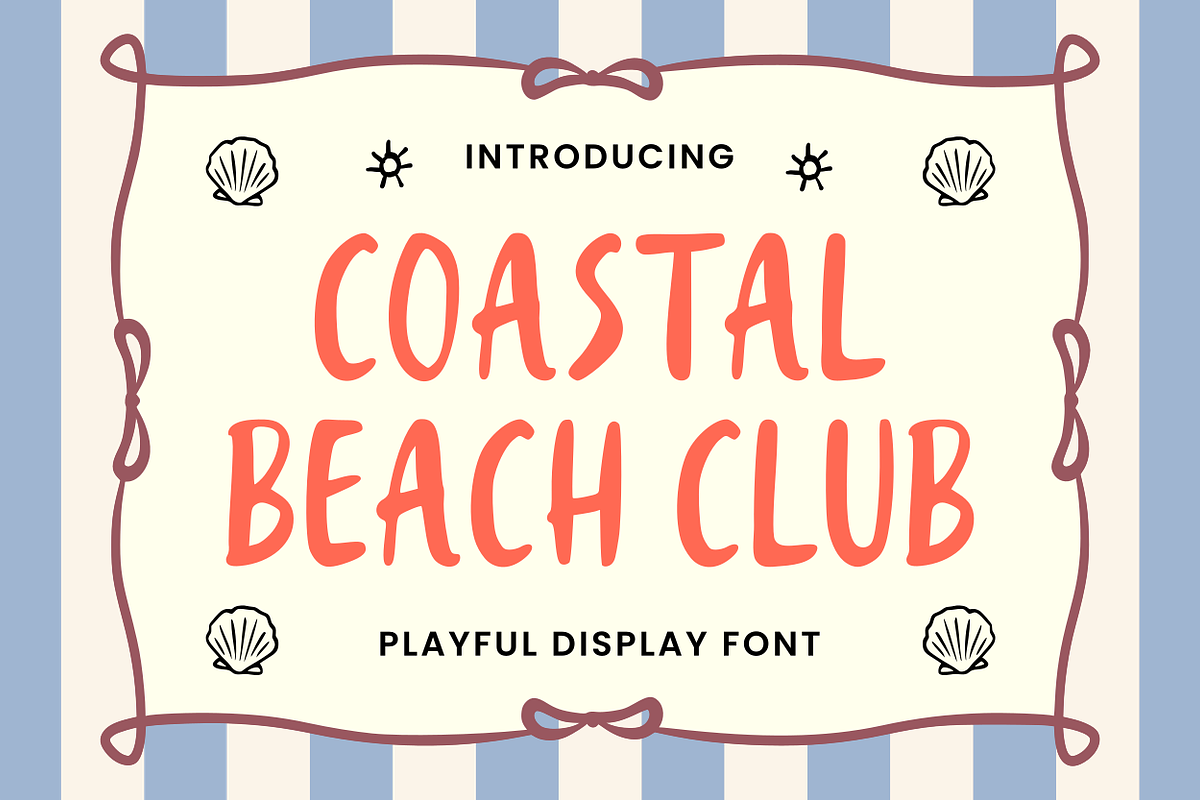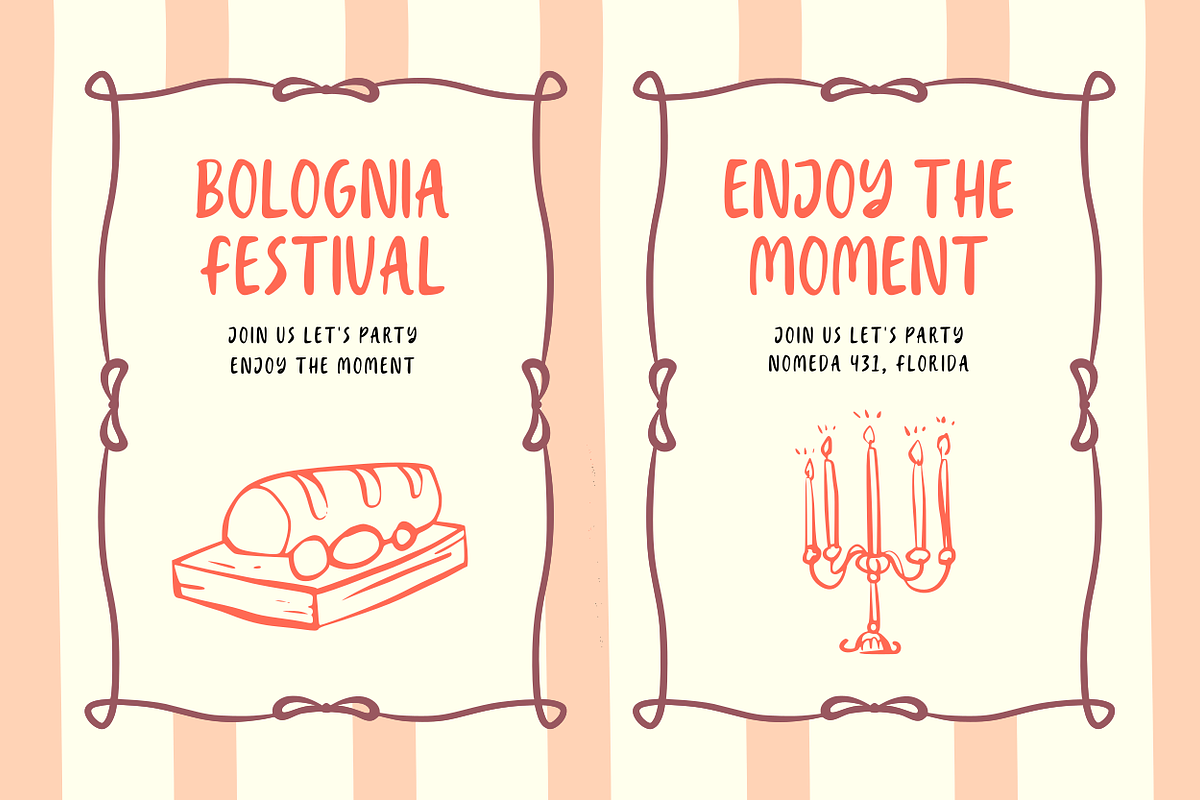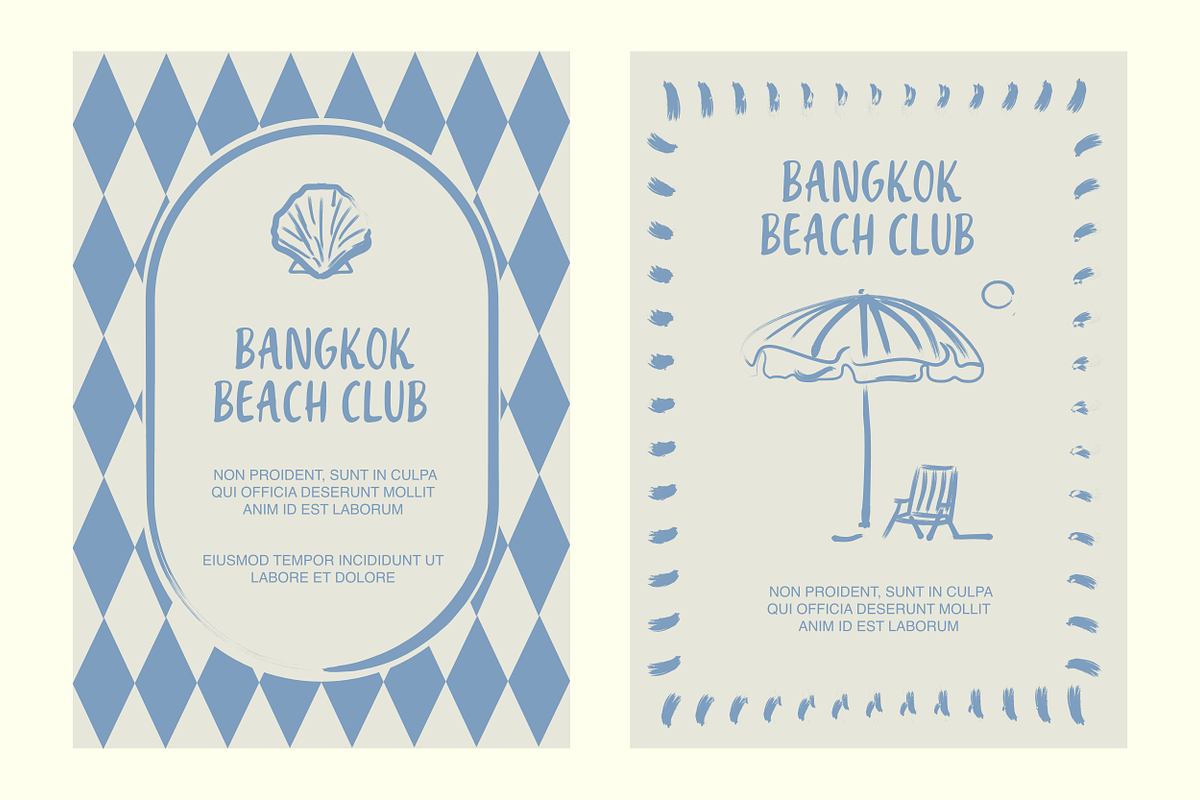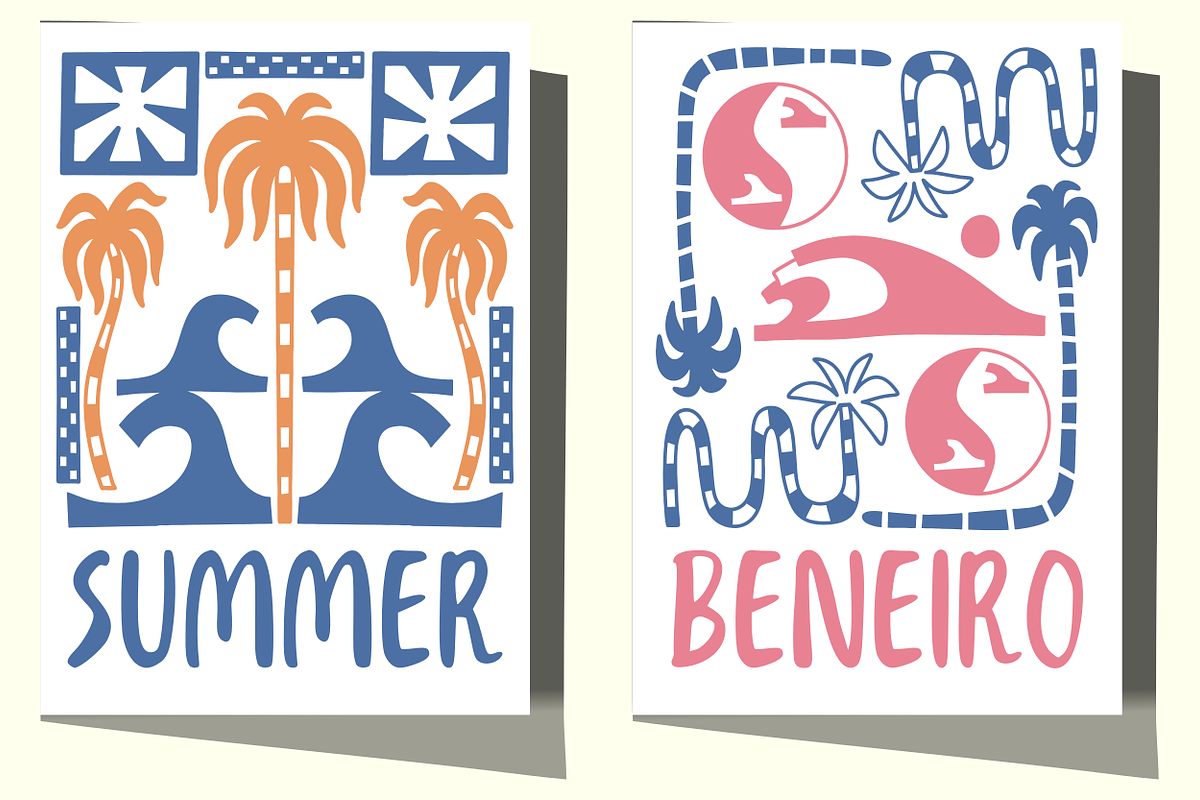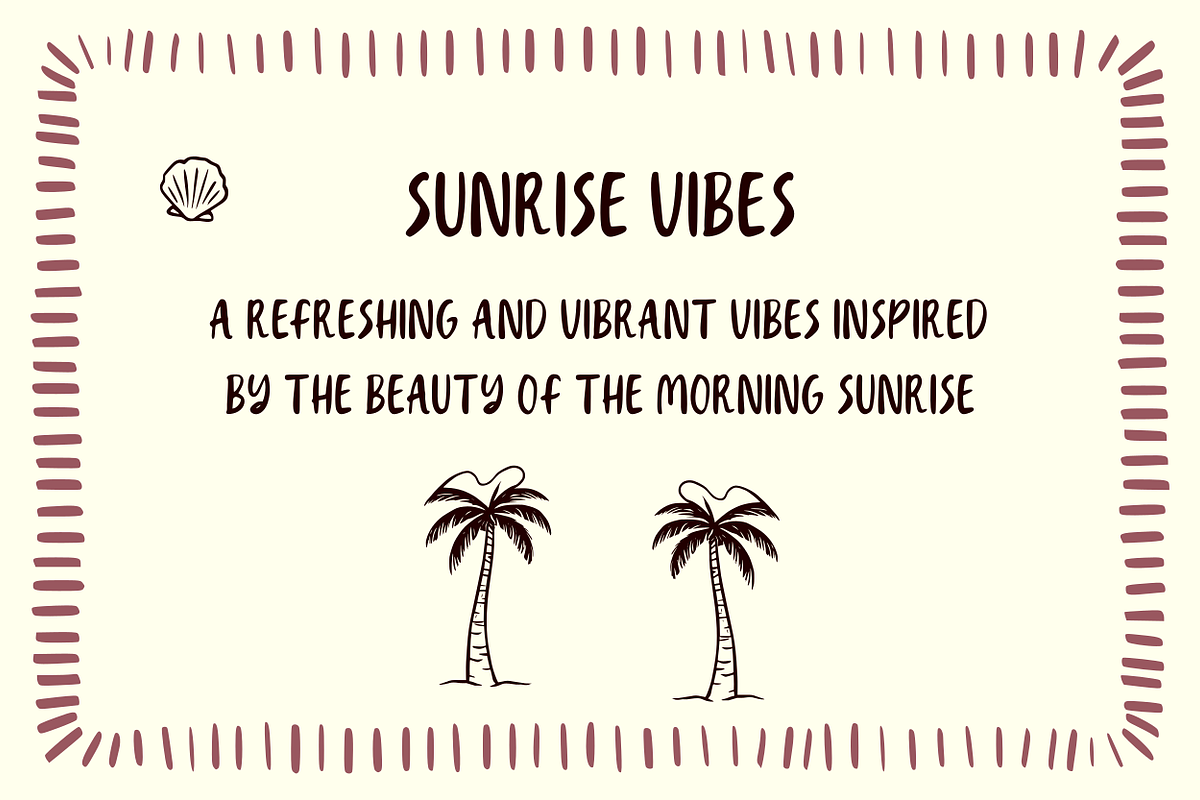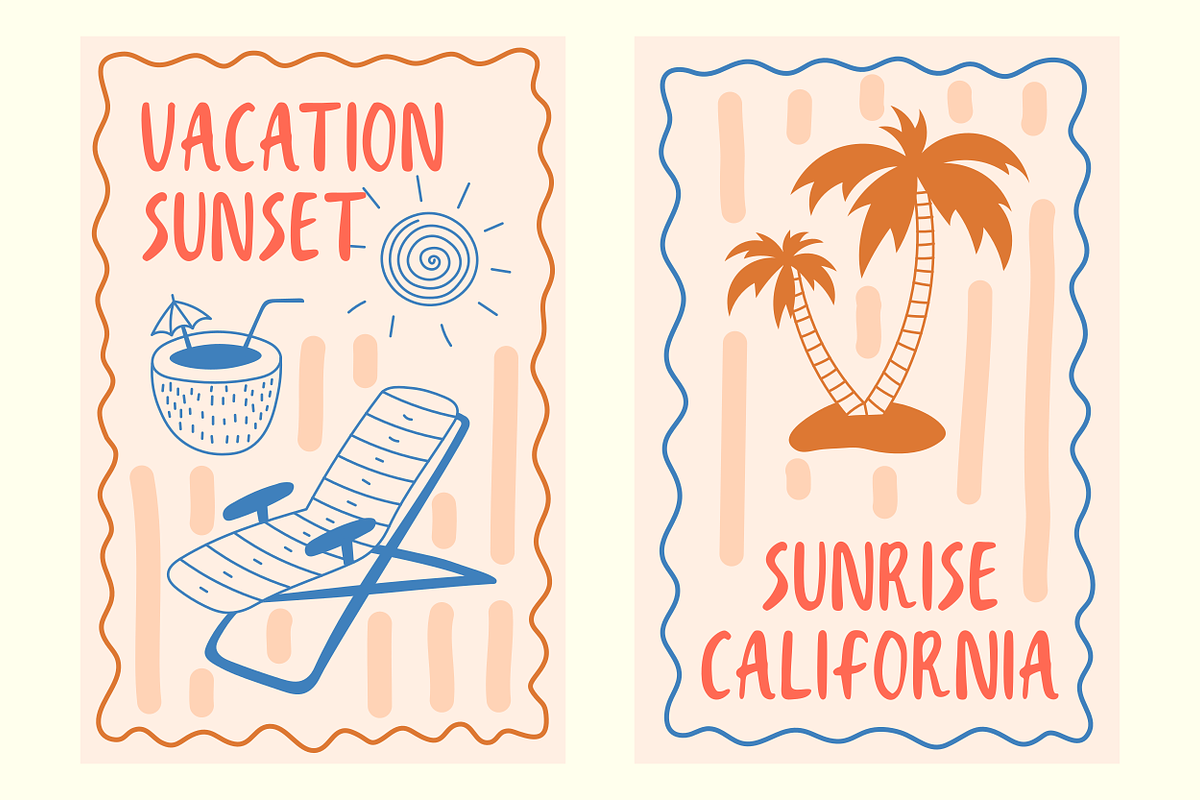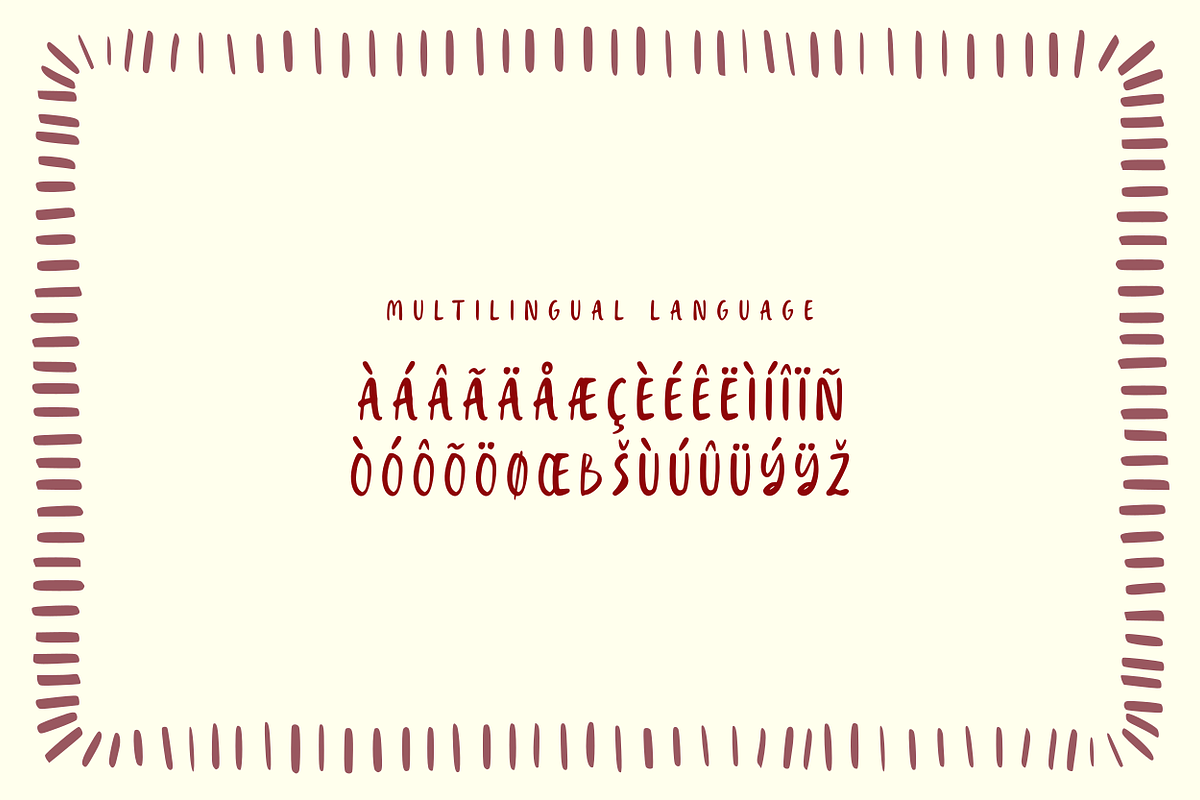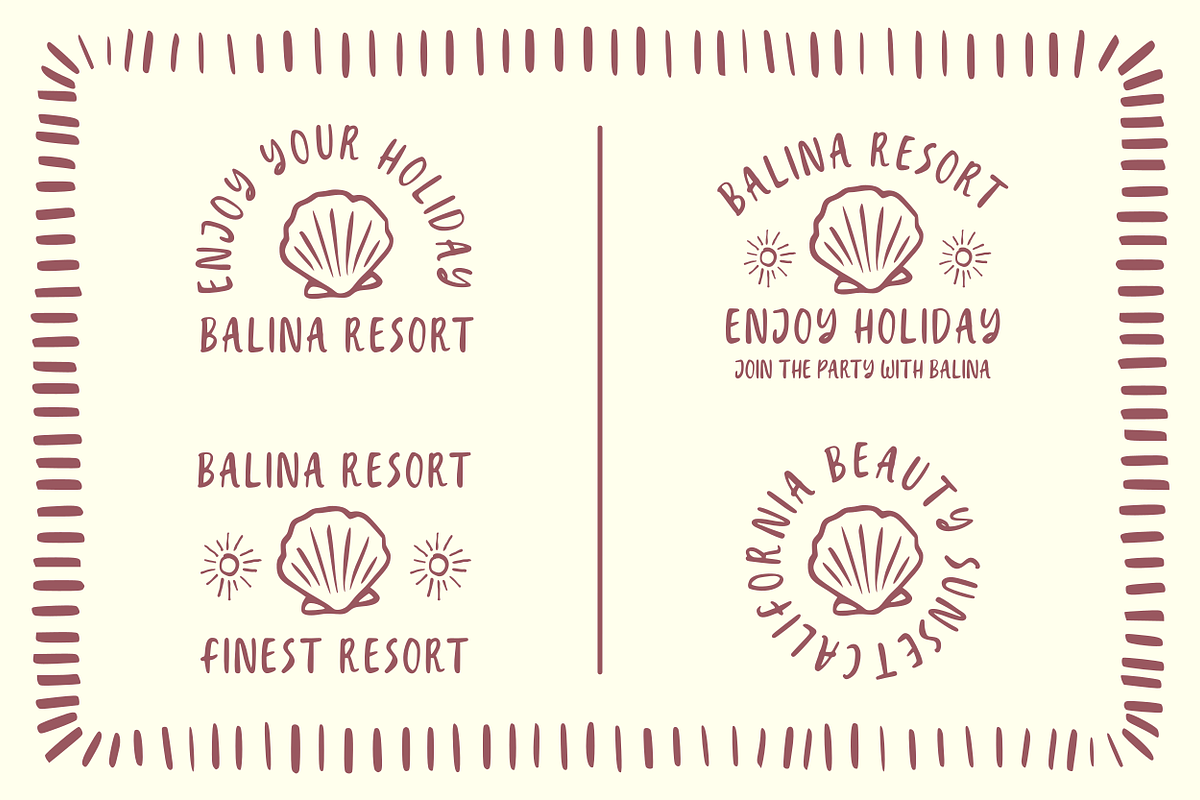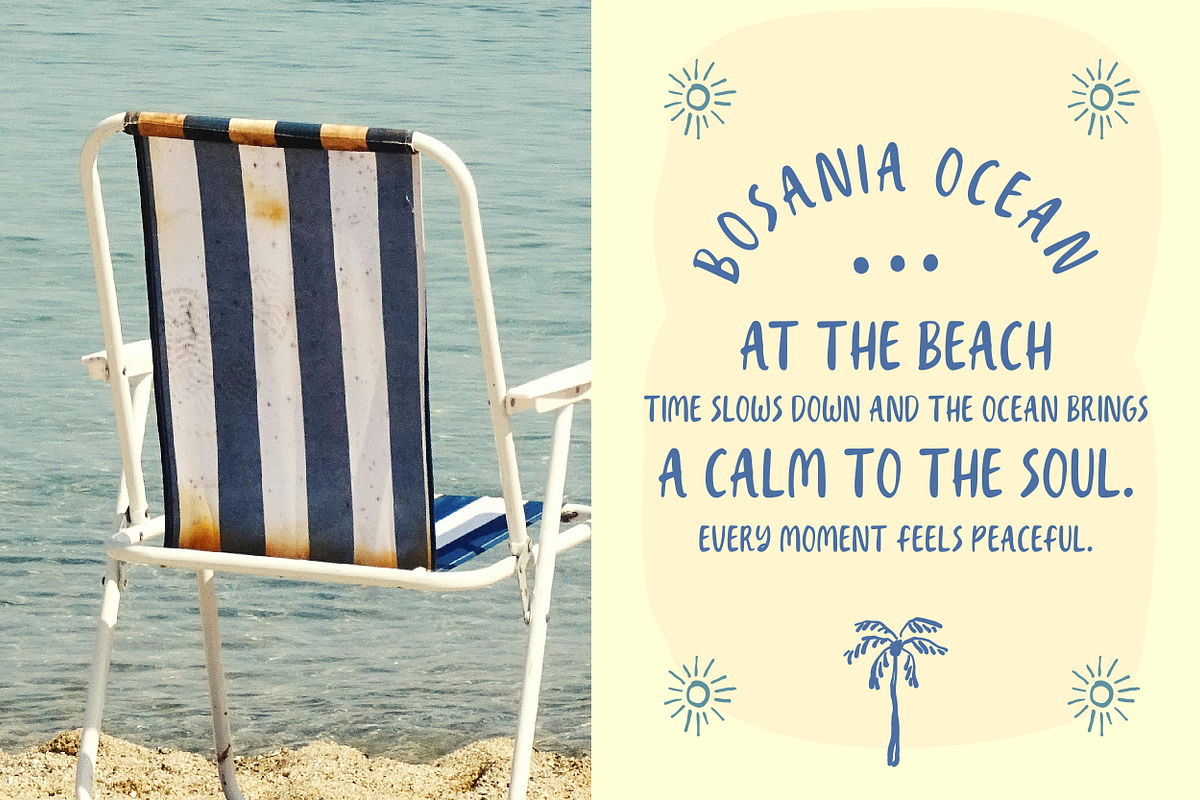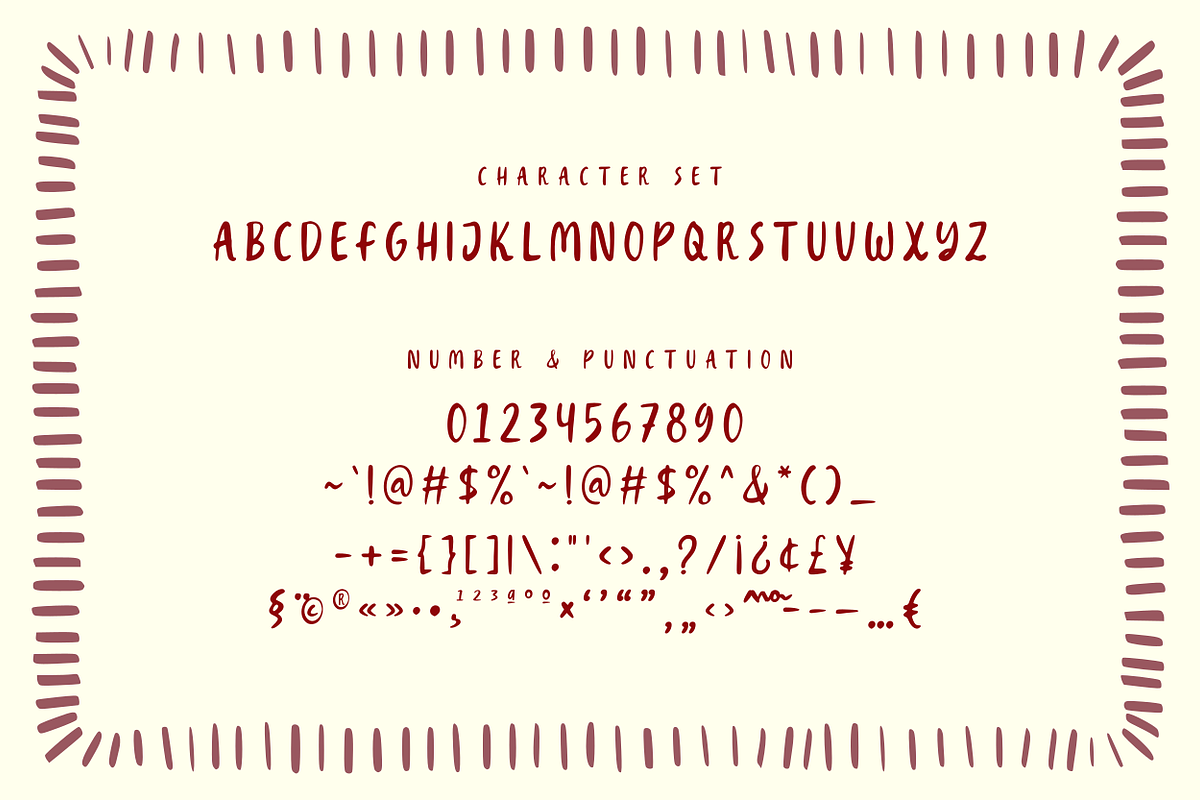
Coastal Beach - Handwritten Display
🌊 COASTAL BEACH – Handwritten Display yang Breezy & Natural 🌴
Capture coastal living vibes dengan font handwritten yang terasa fresh dari pantai. Coastal Beach inject sun-kissed energy ke branding, packaging, dan logo Anda—perfect untuk beach lifestyle brands yang ingin stand out organically.
- Coastal branding & beach lifestyle businesses
- Summer packaging & product labels
- Handwritten logos & apparel tags
- Vacation rental branding & travel content
Quick Perks (Why Designers Love It): ✍️ 201 Glyphs + Natural Handwritten Flow – Authentic beach handwriting 🌍 66 Languages Supported – Global coastal brands ready 🌊 Coastal Aesthetic – Sun, sand, ocean-inspired letterforms 🎨 Display Font Optimized – Bold enough for headlines & packaging